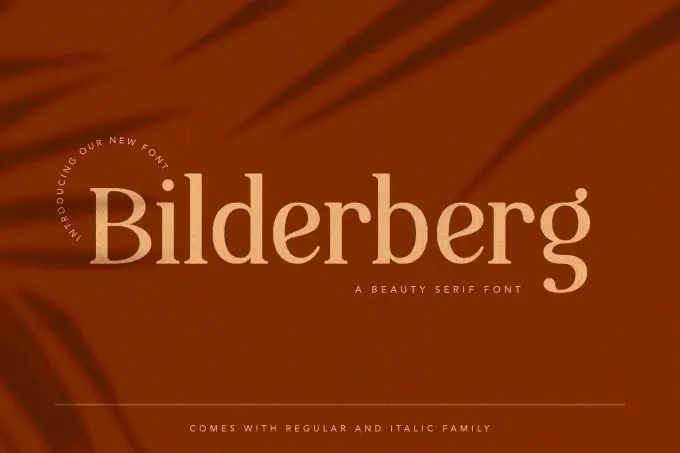
Bilderberg Serif Font – Download Grátis
Bilderberg Serif é uma elegante e sofisticada fonte serif estreita que oferece grande diversidade para seus projetos visuais. Introduzida pelo designer peterdraw na plataforma de criação de recursos 99designs, ela traz dois estilos básicos: regular e itálico. Com o apoio multilíngue, esta é uma fonte moderna e vintage que captura o melhor da simplicidade minimalista e elegantez moderna. Suas linhas finas mas firmes e seu design refinado a tornam uma opção ideal para criar um visual único em suas aplicações. Aproveite tanto os estilos regular quanto itálico, dependendo do ambiente específico de cada projeto que está criando. Com tantos recursos, não apenas é incrivelmente versátil, mas também se adapta bem a linguagens e contextos internacionais. Esta fonte é uma perfeita escolha para qualquer designer em busca de um estilo elegante e contemporâneo.